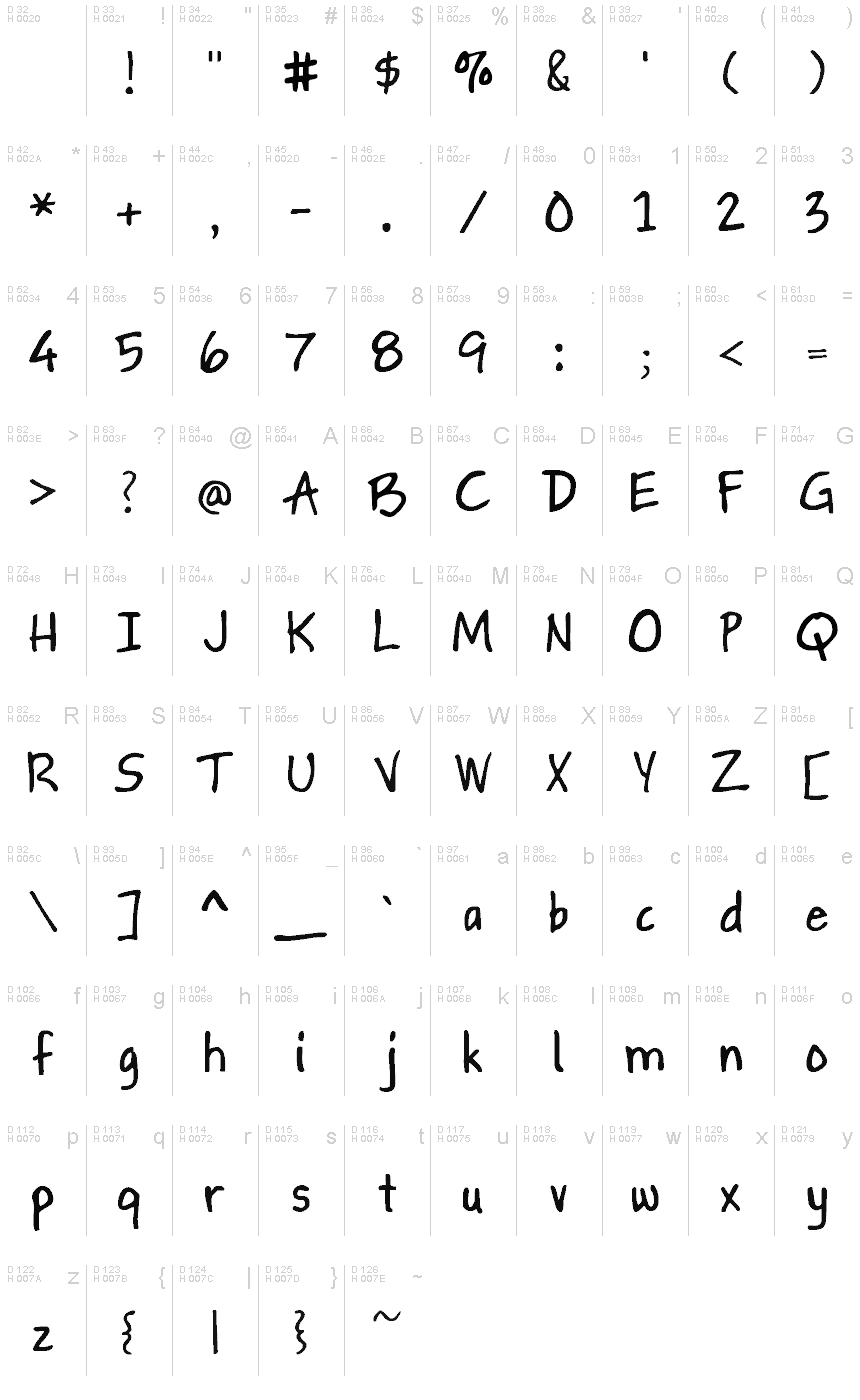
Gapstown Small AH von Fontgrube AH ist eine kostenlose Handschrift-Schrift, die den charmanten, tintigen Look eines echten Filzstifts beibehält, dabei aber auch in kleinen Größen sauber und lesbar bleibt. Die abgerundeten, leicht unebenen Striche wirken zwanglos und menschlich, doch dank der gleichmäßigen und engen Abstände bleibt das Schriftbild auch bei kleiner Skalierung für Beschriftungen oder Notizen stabil. Das Ergebnis ist eine Handschrift, die authentisch und persönlich wirkt, ohne dabei unordentlich oder kindlich zu wirken.
Mit Gapstown Small AH verleihen Sie App-Oberflächen, Chat-Grafiken, Tagebuchseiten, Arbeitsblättern, Etiketten und informellen Postern eine freundliche Note. Diese kostenlose Schriftart eignet sich hervorragend für Projekte, bei denen eine handschriftliche Energie gefragt ist, die sowohl auf Bildschirmen als auch im Druck sofort ins Auge fällt. Kombinieren Sie Gapstown Small AH am besten mit einer schlichten serifenlosen Schriftart für den Fließtext und lassen Sie diese Handschrift-Schrift für Überschriften, Anmerkungen und Callouts wirken.
A handwriting font with informal but not too irregular characters, for those who are kind of tired of the standard
hand printing fonts supplied by Creative Suites and commercial operating systems, the ones you see everywhere. These
are fairly unknown faces and a good alternative.
Gapstown comes in two weights, standard and bold, and in two variants: Gapstown and Gapstown Small. The latter has
wider letterspacing for smaller print sizes. Test for yourself which ones to use at what size.